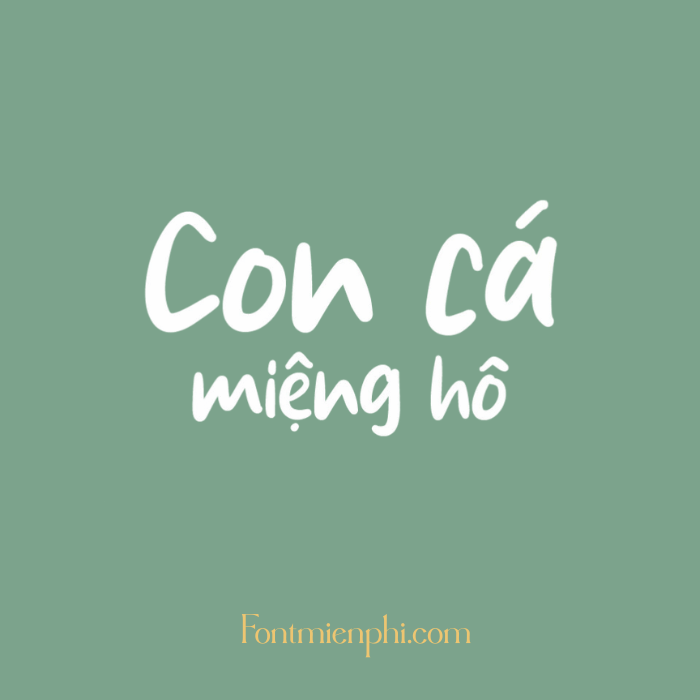
Font Việt hóa 1FTV VIP Original Fish
Font Việt hóa 1FTV VIP Original Fish – Phong Cách Độc Đáo Cho Thiết Kế
Font Việt hóa 1FTV VIP Original Fish là bộ font chữ nghệ thuật độc đáo, được thiết kế dành riêng cho cộng đồng sáng tạo Việt. Với nét chữ cá tính, uốn lượn như dòng nước, font chữ này phù hợp cho các dự án poster, logo, bìa sách, quảng cáo, và thiệp mời. 1FTV VIP Original Fish hỗ trợ đầy đủ tiếng Việt, đảm bảo tính thẩm mỹ và dễ đọc.
Đặc điểm nổi bật:
✔ Thiết kế sinh động – Nét chữ mềm mại, phóng khoáng, tạo điểm nhấn ấn tượng.
✔ Hỗ trợ Tiếng Việt – Đầy đủ dấu, tương thích với mọi phần mềm thiết kế.
✔ Đa dạng ứng dụng – Dùng cho in ấn, digital art, branding, và nhiều mục đích sáng tạo khác.